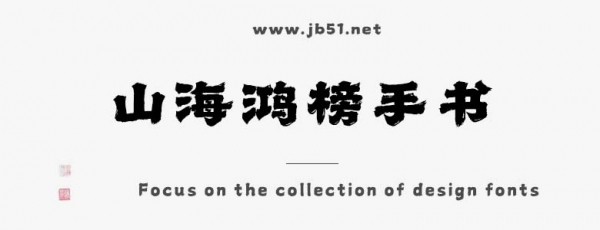
山海鴻榜手書(shū)W是由山海字庫(kù)出品的字體,這款字體筆觸適中,字形端正,具有很好的視覺(jué)感,適合應(yīng)用于藝術(shù)設(shè)計(jì)、平面宣傳設(shè)計(jì)、網(wǎng)頁(yè)設(shè)計(jì),書(shū)法字帖等領(lǐng)域,需要的朋友可以前來(lái)本站下載。